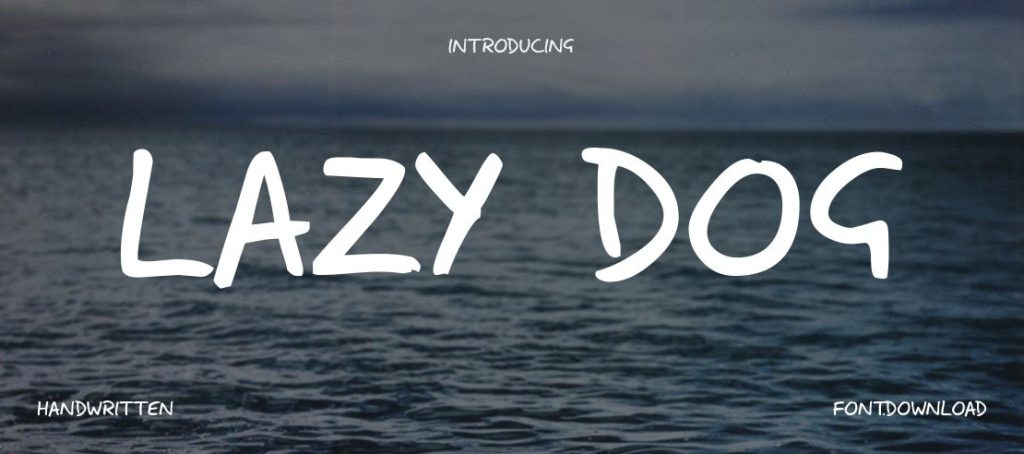
Tác giả: Syafrizal a.k.a. Khurasan
Kiểu chữ: Script – Handwritten
Độ dày: Thin, Regular, Bold
Font Lazydog mang nét chữ độc đáo và tinh nghịch, thường được sử dụng trong thiết kế đồ họa để tạo ra cảm giác thân thiện và vui tươi. Font Lazydog là một